巷でウワサの「テラ豚丼」騒動に関する、吉野家お詫びPDFの話。
フォントは「MS明朝」と「Century」そして謎の「00」というTrueTypeフォントが使われています。
この「00」(フォントメニュー名はきちんと和名がついている…のかもしれません。)というフォント。何に使われているかとい言えばおそらくアレです。アレ。
ヨシノヤと言えば、「つち吉」の字形を保持すべく頑張ってる会社であります。
おそらくこれは、電子文内にて「つち吉」の字形を実現するためのハウスフォント(という用語が正しいか否かはさておき)だと思われます。
この部分だけ、フォントを変えてあるわけですね。
すばらしい根性!
試しに FontForge で開いてみる。
この「AAAAAA+00」というのが、上で出てきた謎の TrueType フォント「00」。中身は「つち吉」(glyph8)と「・」(.notdef)の2つがあるだけで、他はすべて未定義か空白だった。
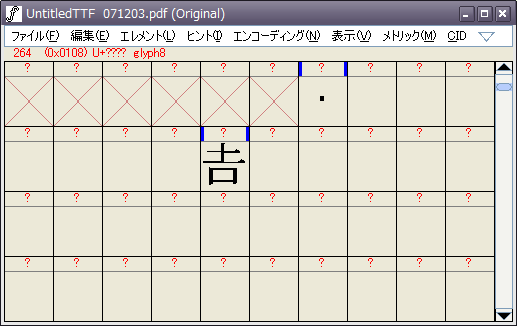
どうもこのフォントは256グリッドで作られている様子。普通は1024程度のものが多い気がするので、これは少ないんじゃ……と思ったら、MS明朝も256だった。ちなみに PostScript フォントでは1000、TrueType フォントでは2の冪乗グリッドが標準らしい。フォント情報は開けなかった。